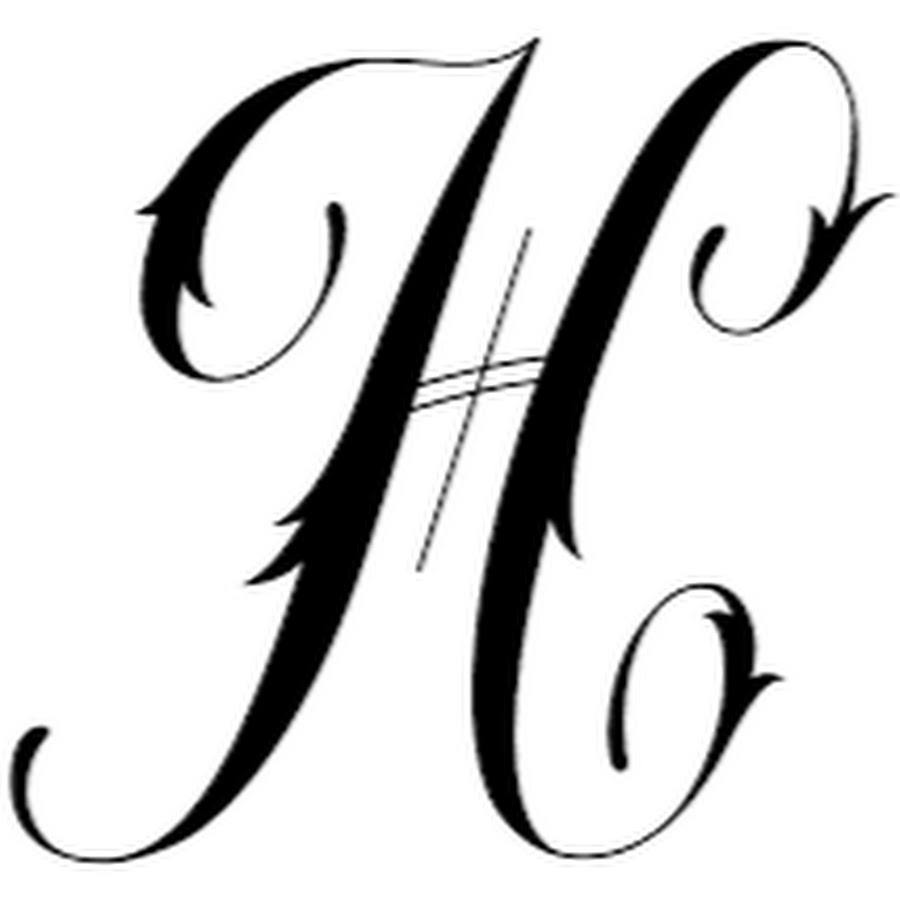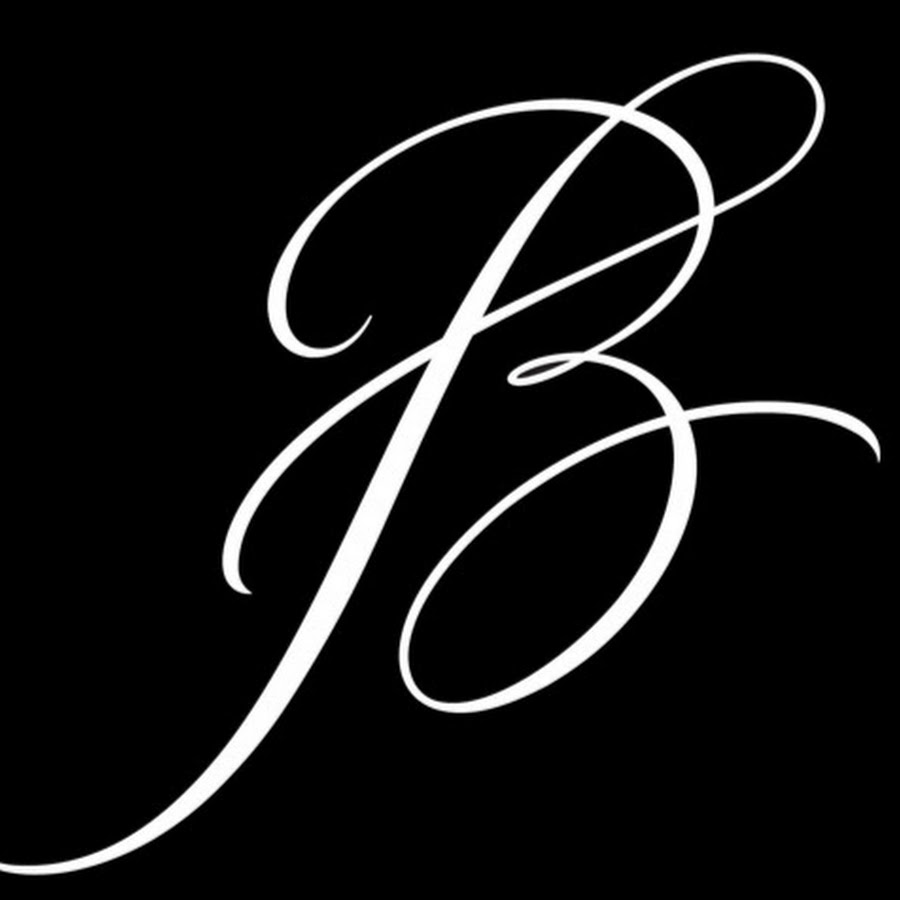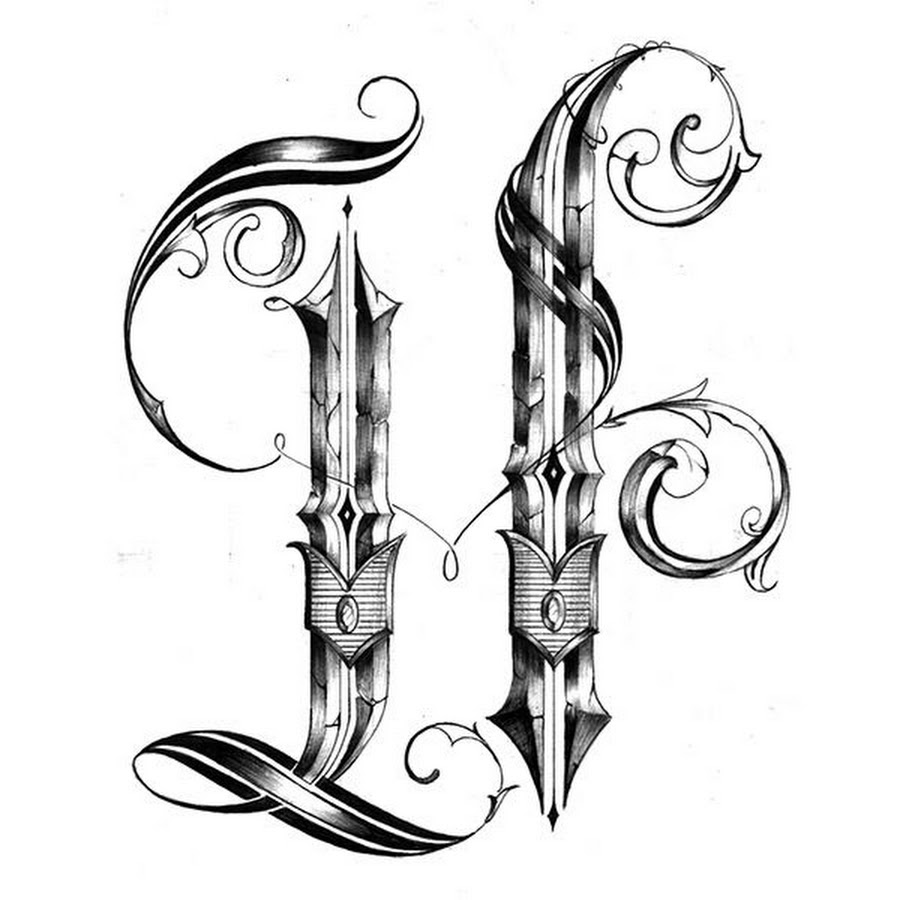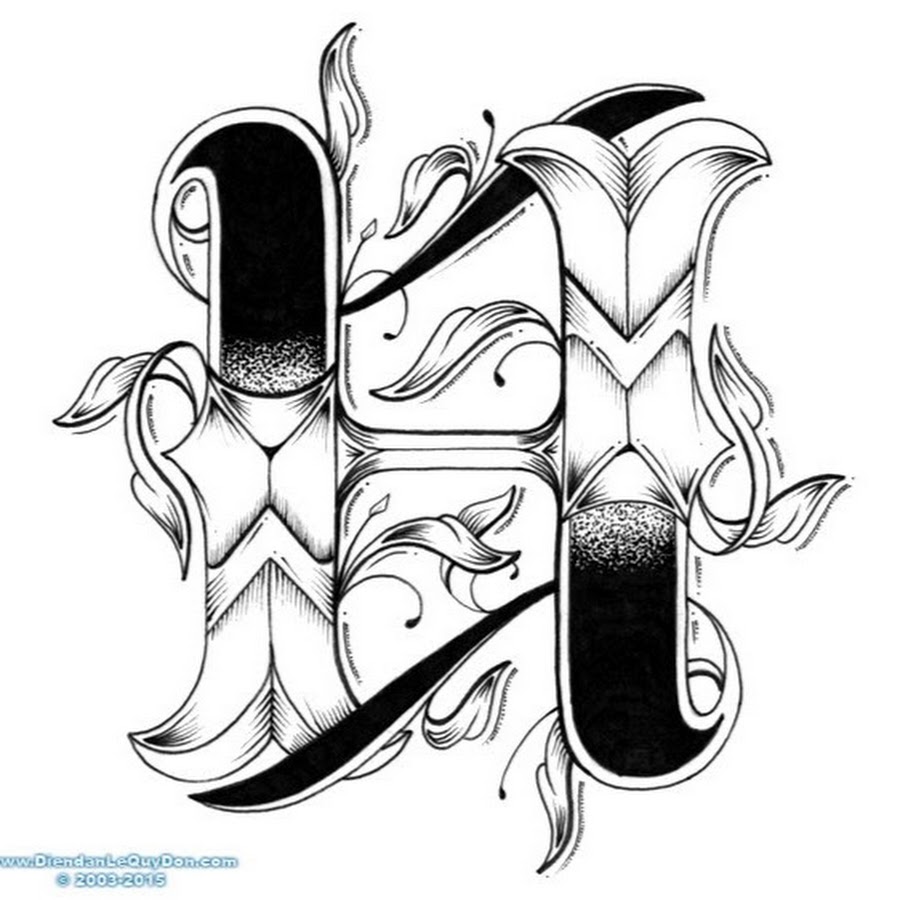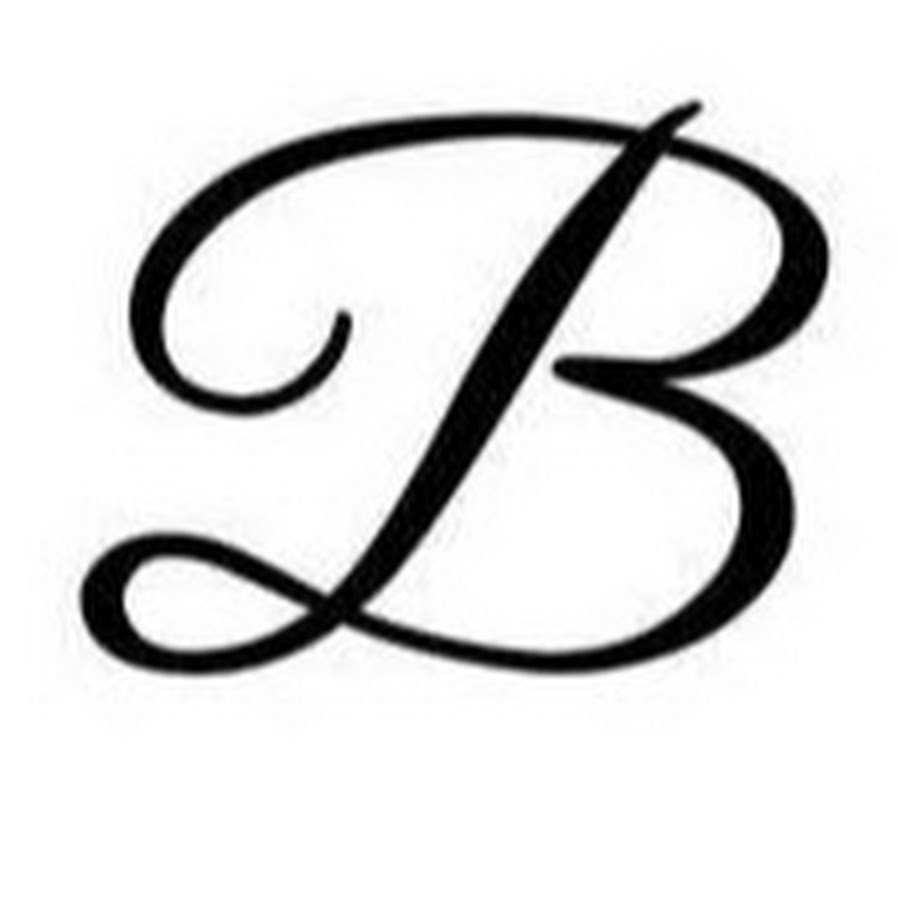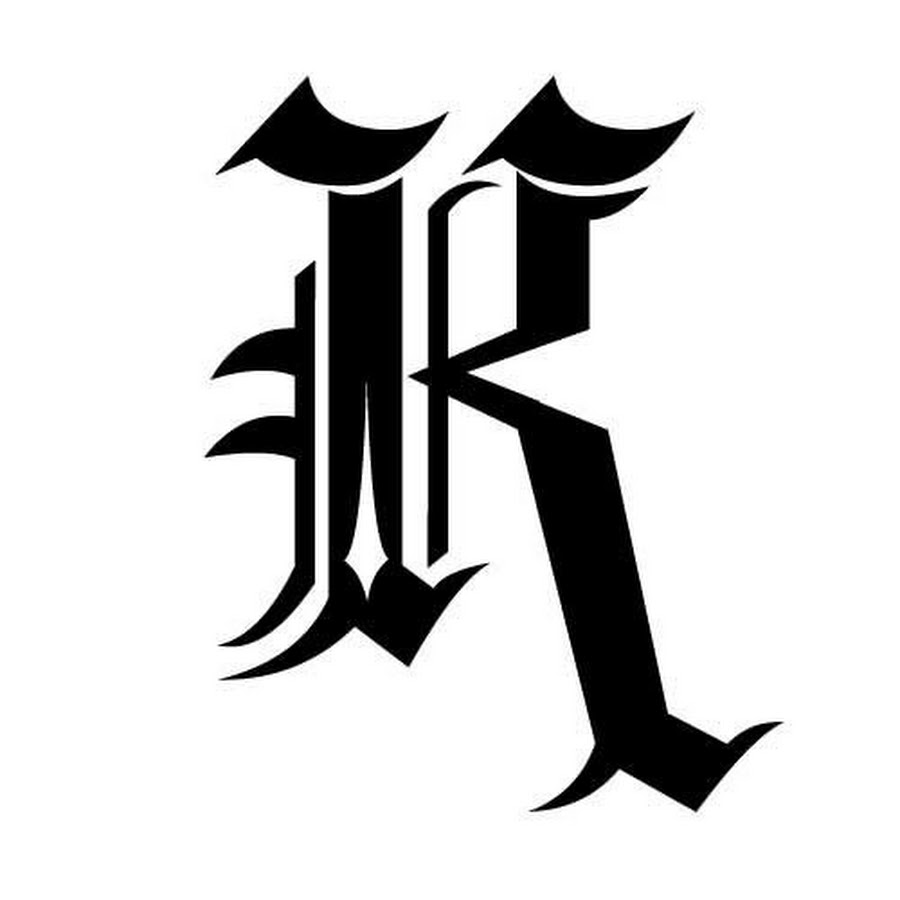
Эскизы тату буквы — классные рисунки для тату в которых есть буквыИнтересная информация про тату и эскизы тату буквы
Каждый человек, желающий набить себе татуировку в виде буквы, должен, в первую очередь, выбрать ее эскиз и место, где она будет расположена. Специалисты в этом случае предлагают руководствоваться собственными желаниями и вкусами. Например, некоторые люди предполагают, что первая буква их имени или определенный символ, иероглиф или руна может принести удачу; другие же предпочитают обзавестись фразой, которая определяет их жизненный путь. Есть и люди, которые желают в качестве тату набить памятную дату.
В истории татуировкам в виде букв давали противоположный смысл. Обычно так клеймили преступников, как, например, делали это во Франции. Буква «V» означала не пресловутую «vendetta» или «victory», а знак вора; «F» говорила о том, что ее носитель был фальсификатором и обманщиком; буквосочетанием «GAL» клеймили тех, кому суждено оказаться на галерах, а «TFR» обозначало, что ее носителя ожидали исправительные работы. Татуировали даже в армии: буквами «BC» указывали на дезертиров – это повышало дисциплину среди солдат.
Современные варианты эскизов и рисунков для букв в татуировке
Однако в наши дни татуировки в виде букв наносятся обычно в память о любимых людях или знаменательных датах. Большое значение при этом имеет именно стиль оформления. В этом плане обычно популярны каллиграфические стили, которые процветают на Востоке и особенно в Китае. Татуировка с буквами может красивой резной надписью украшать часть тела, а может быть незаметным напоминанием только для своего владельца.
Буквы в виде тату очень капризны, поэтому основное, что нужно выбрать – это шрифт, ведь при неправильном надпись может стать нечитабельной или непонятной. Также нужно определиться с местом нанесения тату и его размером. К тому же, не стоит забывать о том, на каком языке следует сделать надпись. Наиболее оптимальным считается нанесение надписи на английском языке, так как он является «общемировым», плюс буквы английского алфавита выглядят эстетичнее букв кириллицы. Также популярными остаются всевозможные китайские иероглифы.
Мужчины предпочитают наносить печатные, «строгие» буквы с широкими линиями и заострёнными кончиками. Женщины же любят тонкие, изящные линии с дополнительными узорами в виде декора. Шрифт, с помощью которого наносятся буквы, должен быть читаемым и не иметь слишком тонких и близко расположенных друг к другу линий. Тату имеет свойство со временем размываться, поэтому слишком мелкий шрифт рискует стать просто пятном.
Красивый шрифт на ноге
Различные вариации шрифтов позволят сделать татуировку в виде надписи красивой и оригинальной
Особенности татуировки шрифты
Татуировки в виде надписей смотрятся очень оригинально и красиво.
Их очень любят наносить на свое дело голливудские звезды. В некоторых случаях надпись способна передать смысл татуировки даже лучше чем рисунок. Для этого очень важно подобрать правильный шрифт. Для женских надписей подойдут шрифты с глубокими изгибами, тонкими линиями и дополнительным декором. Для мужских надписей нужно обратить внимание на печатные буквы, применение жирного начертания, заостренные окончания. Татуировки шрифты, значение которых больше зависит от смысла самой надписи, одинаково распространены, как среди женщин, так и среди мужчин.
Выбираем язык и дизайн заглавной буквы
Как правило, шрифт зависит от языка. Однако наибольшей популярностью пользуется английский язык , поскольку он считается мировым. Для татуировки надписи, как правило, выбирают шрифты с вензелями и каллиграфические шрифты. Перед нанесением на свое тело надписи нужно определиться: будет ли это слово или целая фраза. Если вы хотите сделать надпись, которая начинается с заглавной буквы, то нужно обсудить с дизайнером ее особенности, поскольку не каждая заглавная буква будет хорошо смотреться.
Шрифт для татуировки в виде надписи может быть самым разным. Если вы сомневаетесь в выбранном стиле, лучше посоветуйтесь с дизайнером.
Каллиграфические шрифты
Рукописные шрифты для тату подыскать поможет онлайн подбор . Надпись, выполненная с использованием рукописного шрифта, будет неповторимой и всегда актуальной. Не стоит забывать, что лишняя черточка, размер слова или наклон буквы, не говоря уже о дополнительных элементах, завитках, узорах и т.д. может повлиять на общую картинку и даже на восприятие смысла.
Готический шрифт